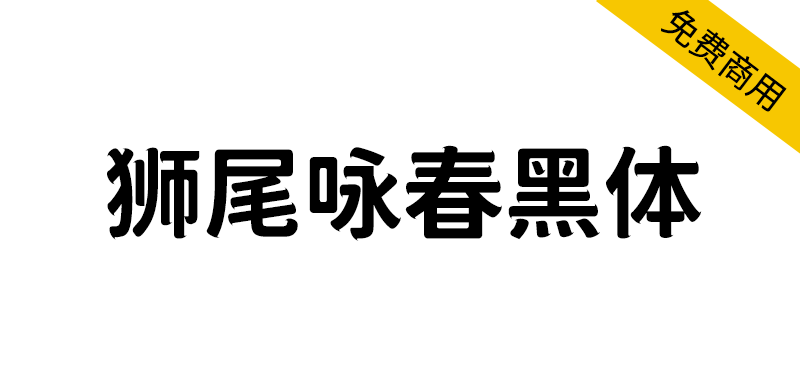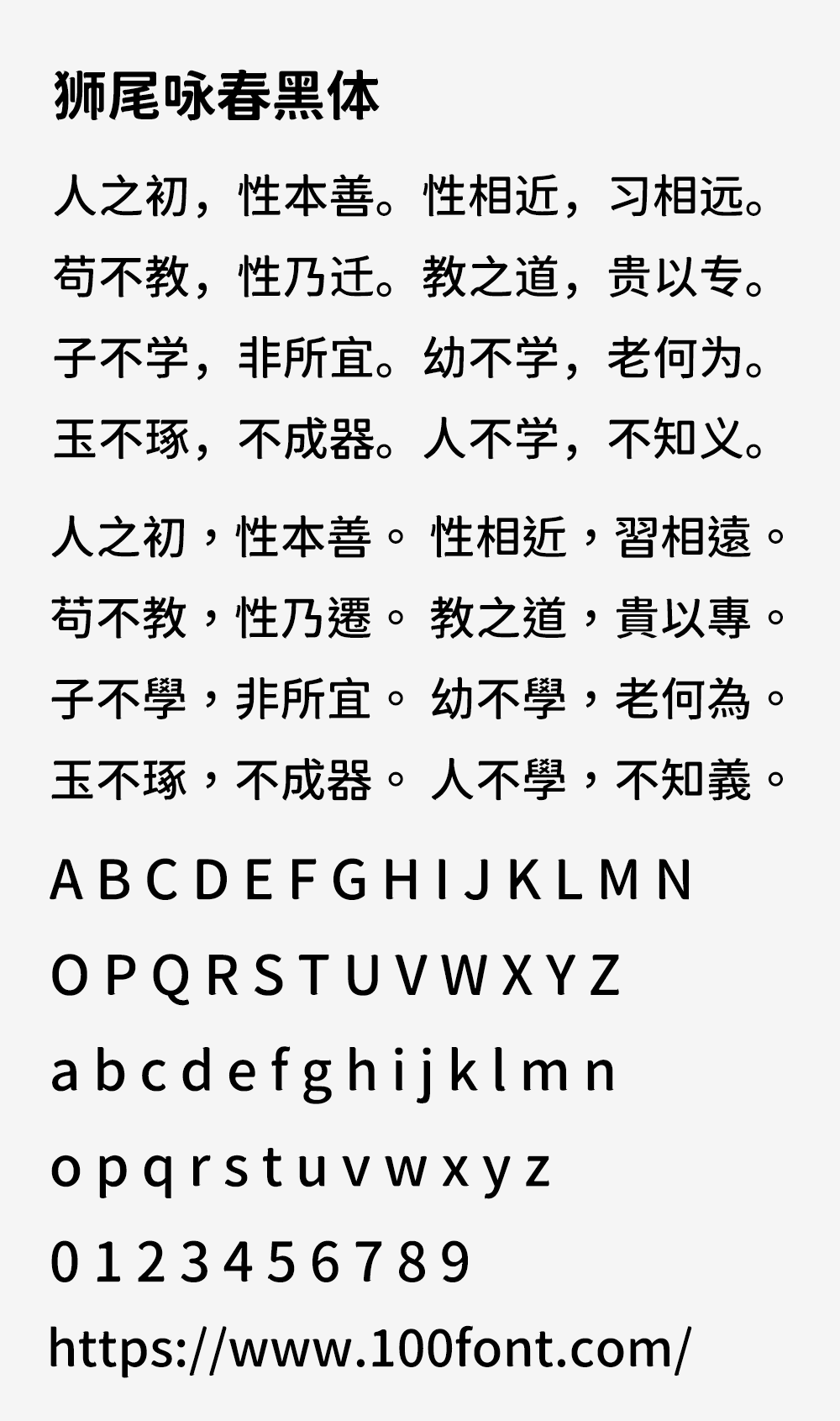
狮尾咏春黑体基于思源黑体的笔触长角和拔脚改造,更加简明现代化的字体。狮尾咏春黑体的特色是笔触长角,起头与收尾有俐落感。狮尾咏春黑体设计上针对笔画粗细支持7种字重,所以不论大标、小标、简单的段落排版都能清晰辨识。支持简体中文、繁体中文、韩文与日文,可以免费商用,欢迎大家自由应用、自由优化、自由改作!
狮尾咏春黑体与「狮尾咏腿黑体」差别在有没有拔脚,「拔脚」就是会有较少的笔画,例如移除「口」字的左右下角会多出的短线条。有拔脚的字会较圆,但是会造成有些字因直接去掉腿后左右不平衡、左右不对衬的「悬空」问题。改使用「腿」系列字体就不会有这个问题。